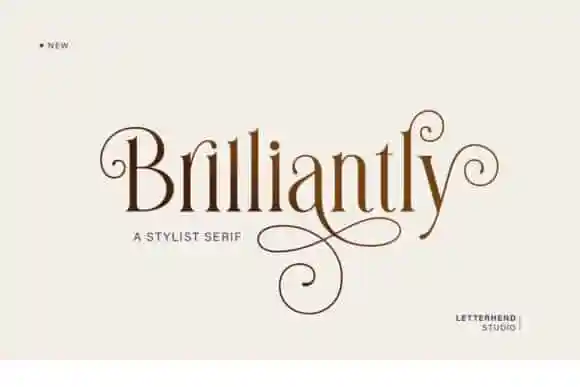
Brilliantly Serif Font – Fonte Grátis
Brilliantly Serif Font
A Brilliantly Serif Font é uma elegante tipografia serif que combina modernidade com um ar autêntico e único. O estilo display dessa fonte oferece alternativas distintas, tornando seus títulos ou logotipos ainda mais atrativos e interessantes. Designada pela designer 99designs, a fonte apresenta muitas alternativas com swashes que proporcionam uma mistura harmônica entre o equilíbrio da serif clássica e os detalhes fluidos dos swashes. A tipografia mantém um ar limpo e organizado, destacando-se como algo singular no campo das fontes serif. Ideal para criações visuais que buscam unir sofisticação com originalidade.